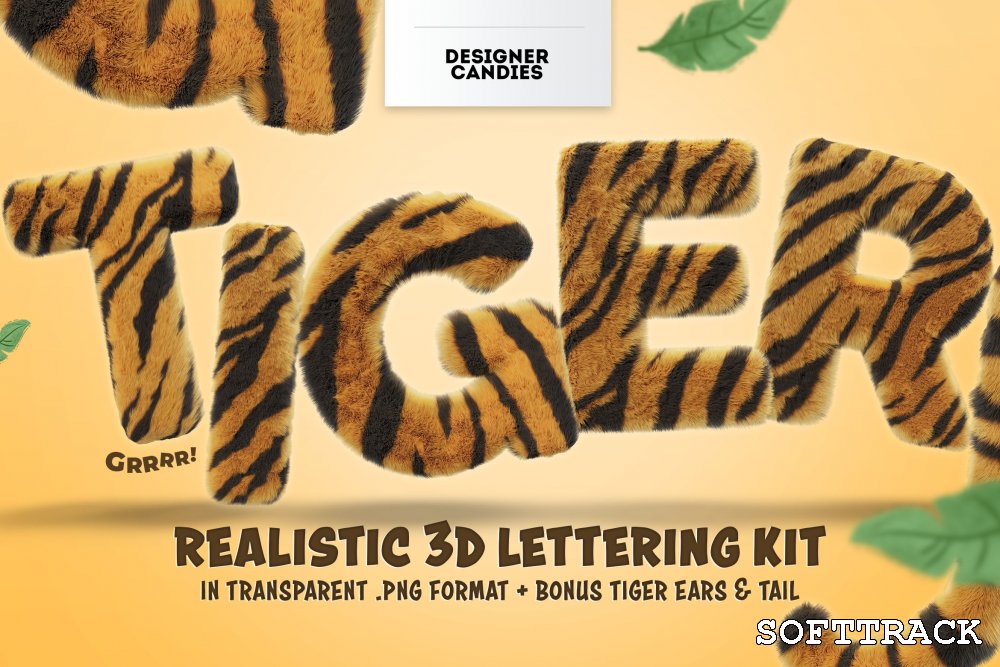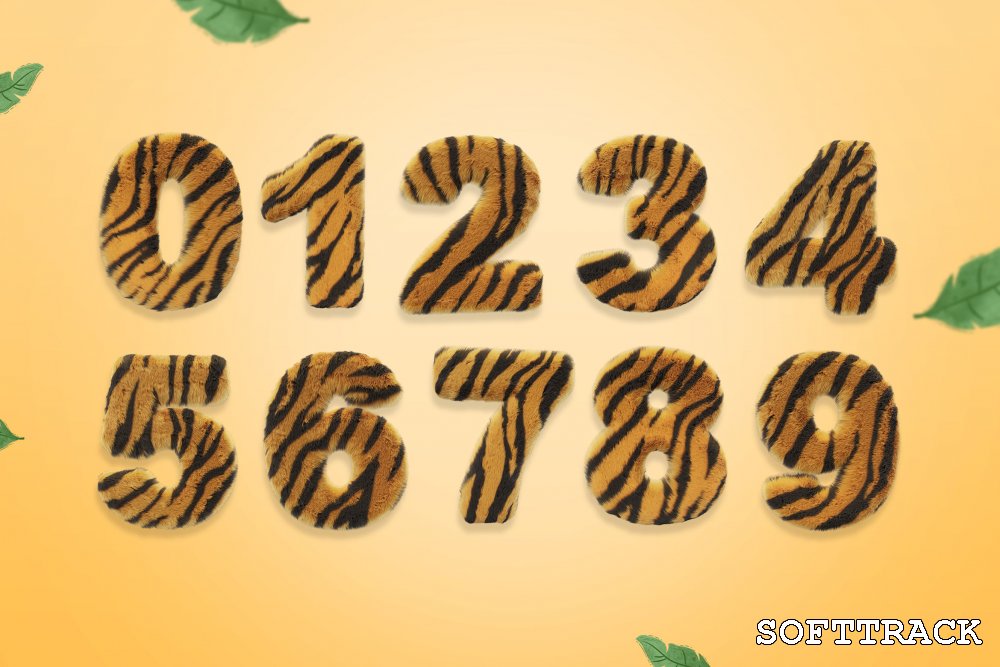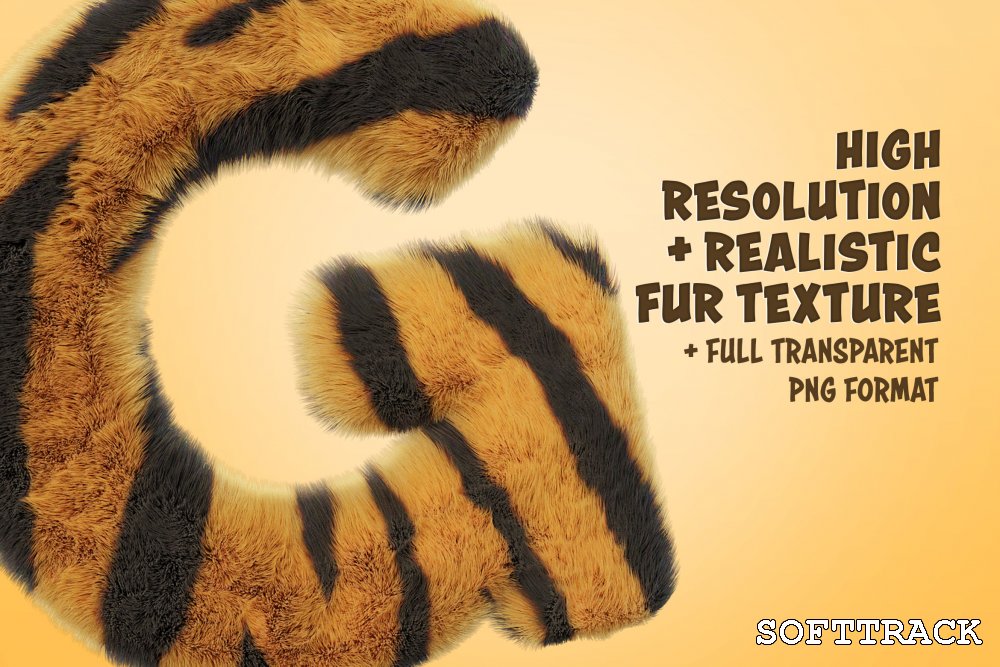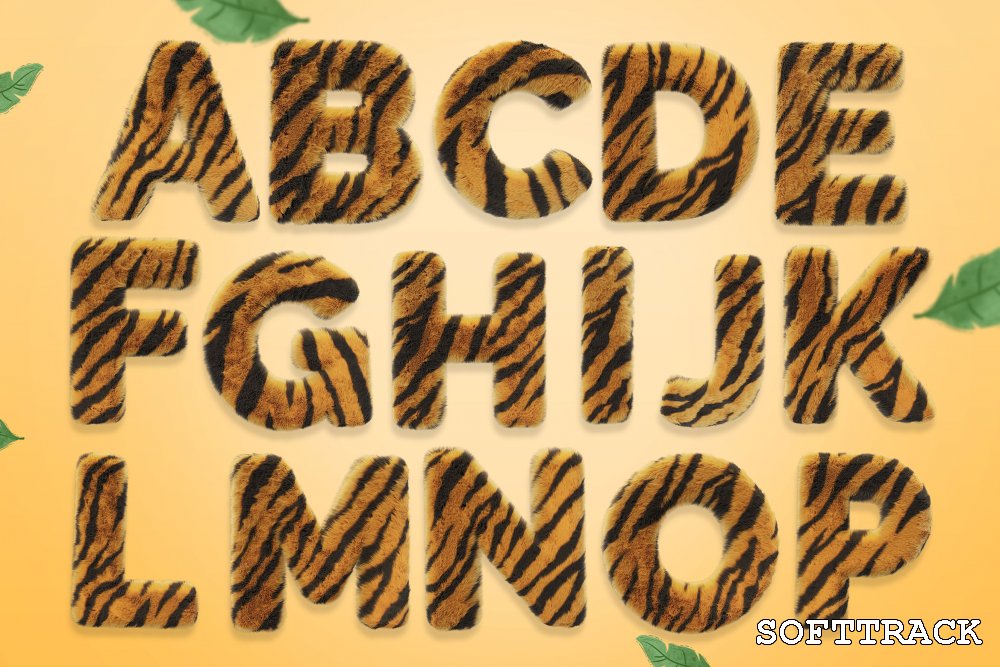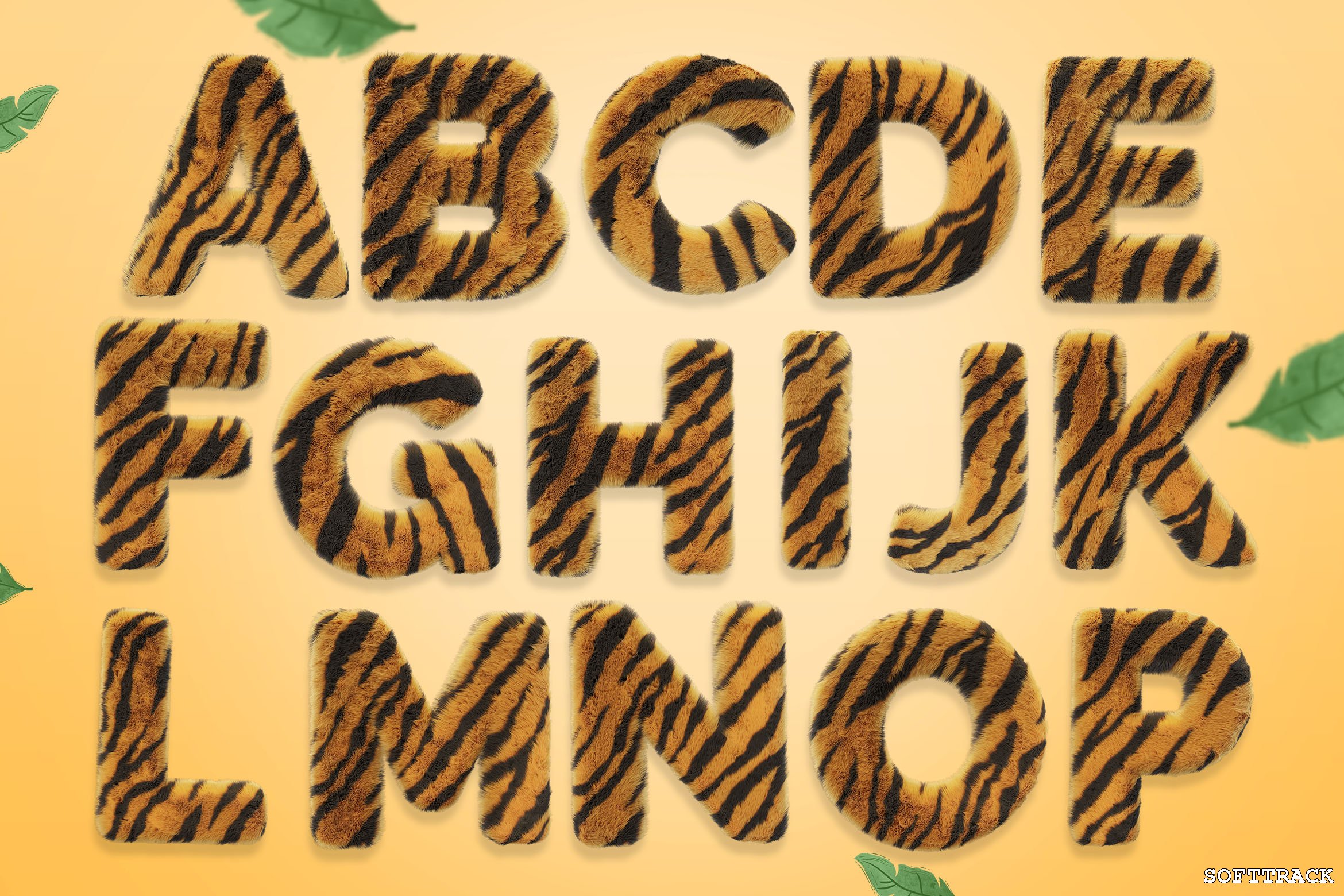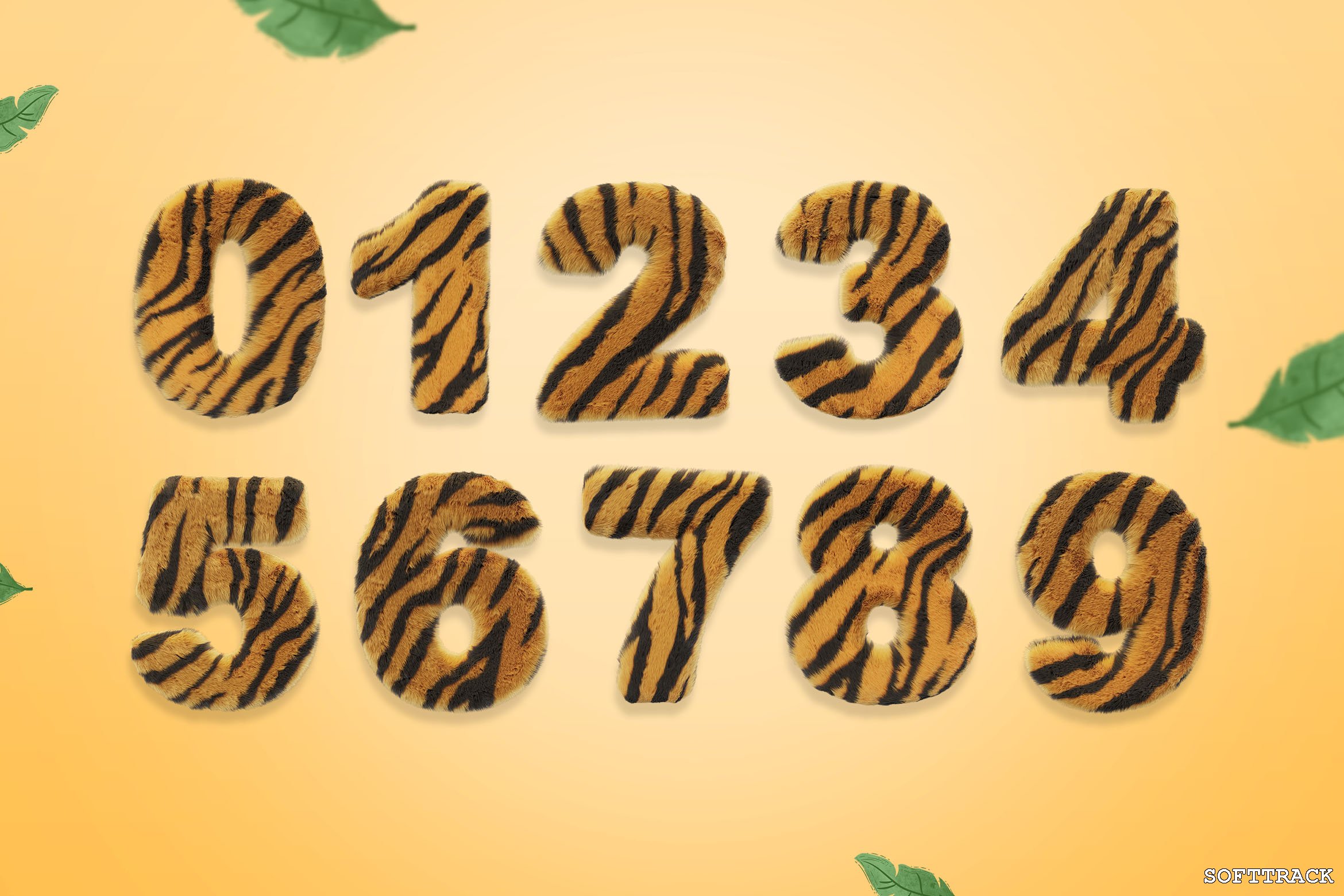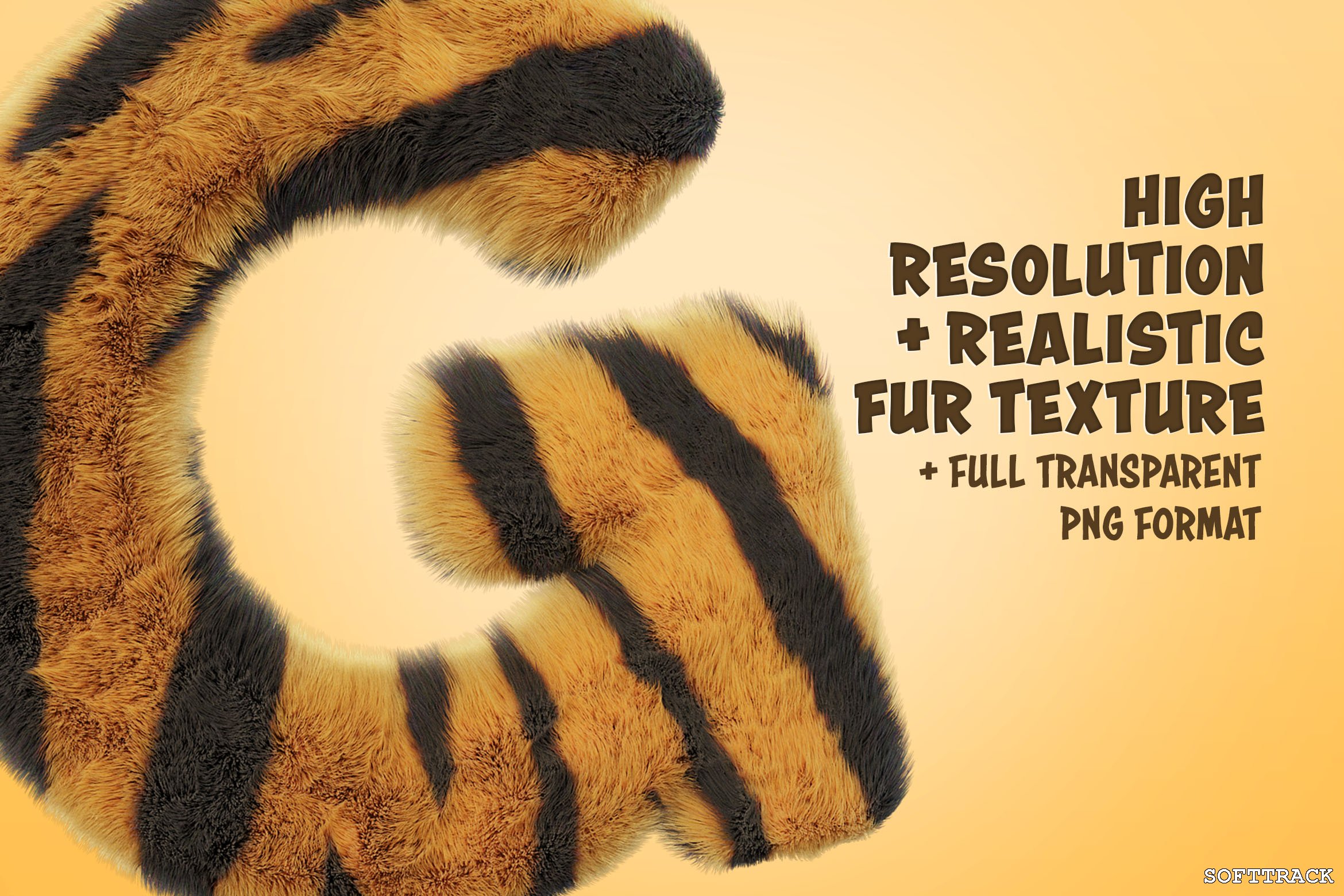
Laat je wilde kant zien met deze ongelooflijke 3D-letterset met tijgerhuid patroon als thema.
Als je ons al een tijdje kent, weet je dat we graag 3D-lettersets maken . Vandaag hebben we voor u een ongelooflijke 3D-letterkit met Tiger Print-textuur, wat resulteert in een letterkit die een wandeling op de wilde kant heeft gemaakt.
gebaseerd op dezelfde ongelooflijke 3D-texturen als ons Animal Print Patterns Pack Deze beletteringset met tijgerhuid is en is ideaal voor projecten met een natuur- of jungle-thema.
Letters AZ
Cijfers 0-9
Bonus: tijgeroren en tijgerstaart